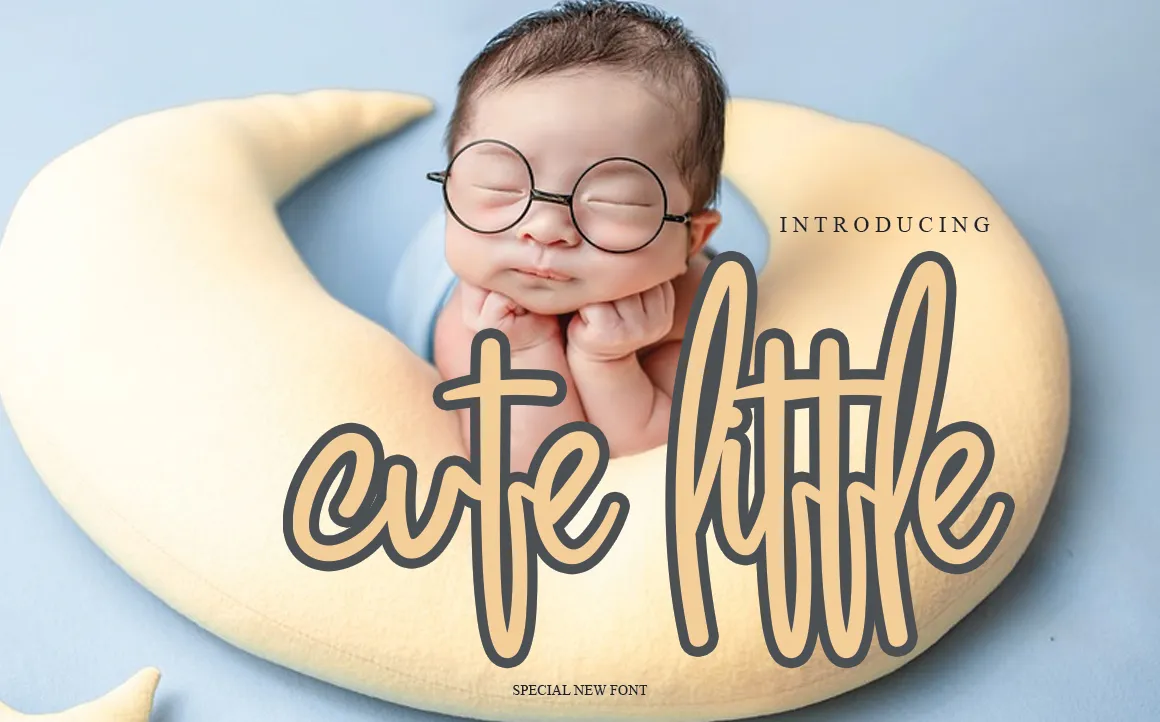
Aqui está uma versão adaptada do texto solicitado, mantendo a essência do design original sem inovar: Esta é uma fonte escrita à mão única e divertida. Ideal tanto para projetos de Instagram quanto para decorar scripts artesanais em DIY. Esta fonte transformará qualquer ideia criativa num trabalho de arte verdadeiro! Composta por linhas levemente onduladas, o cuidado com a tipografia proporciona um toque descontraído que se adequa perfeitamente tanto para projetos pessoais quanto para aplicação em materiais impressos. Esta fonte é certamente uma opção ideal para designers e criativos querendo dar um toque especial aos seus trabalhos, tornando-os ainda mais únicos. A fonte ‘Cute Little Font’, desenvolvida pelo designer levincreative para a categoria de fonts escritas à mão, é o seu complemento perfeito. Não hesite em experimentar – ela certamente enriquecerá seu trabalho e dará um toque especial à sua produção digital ou impressa.